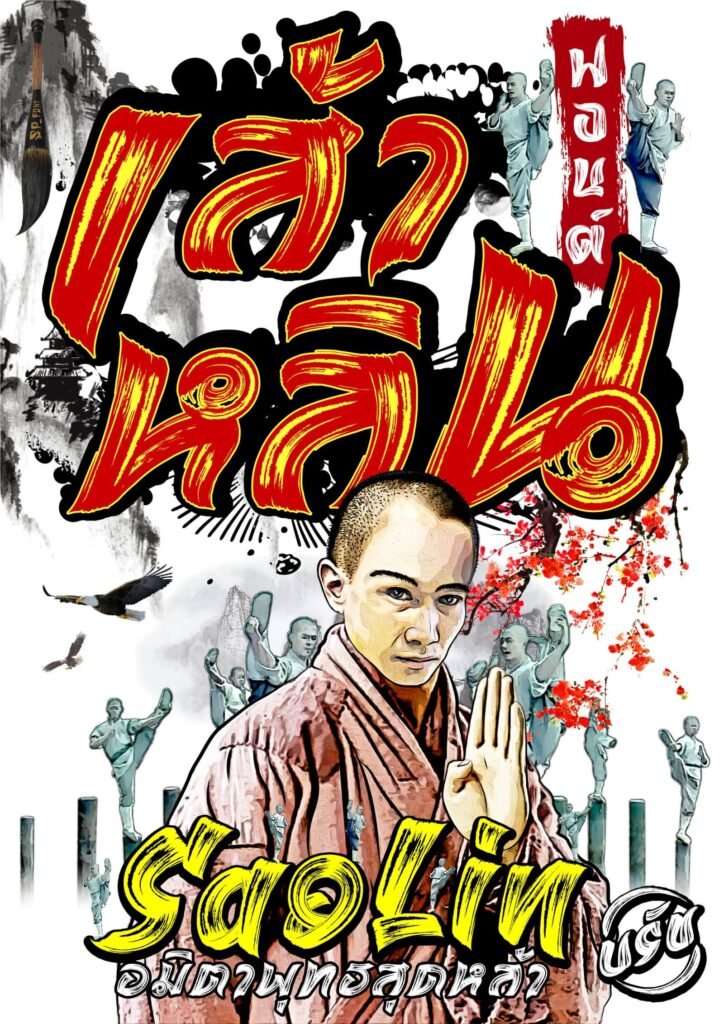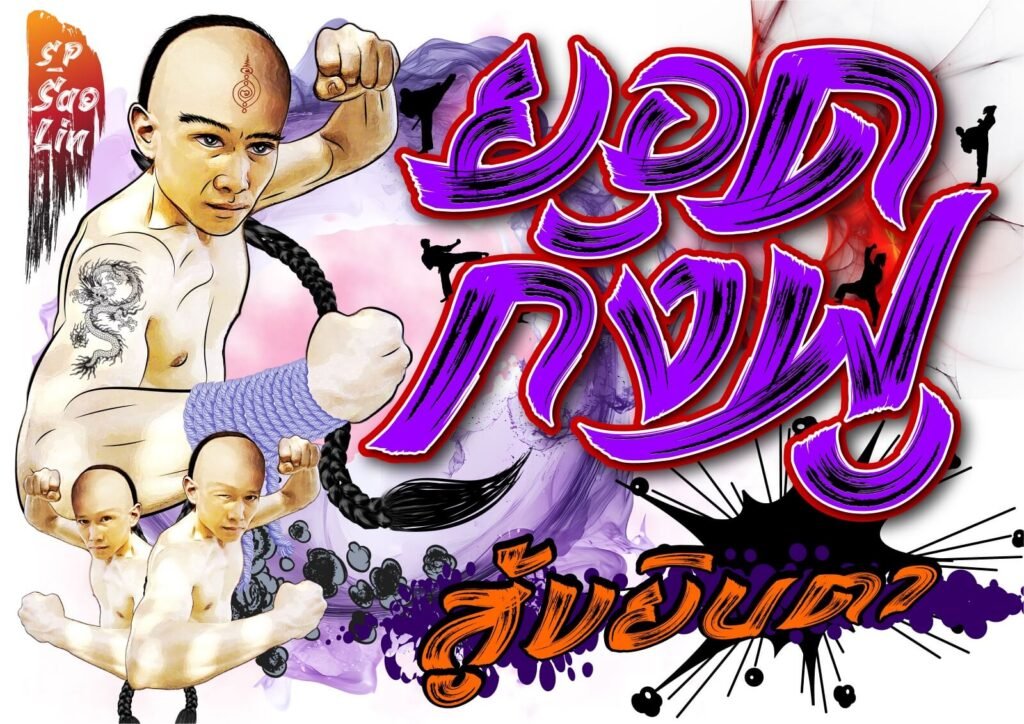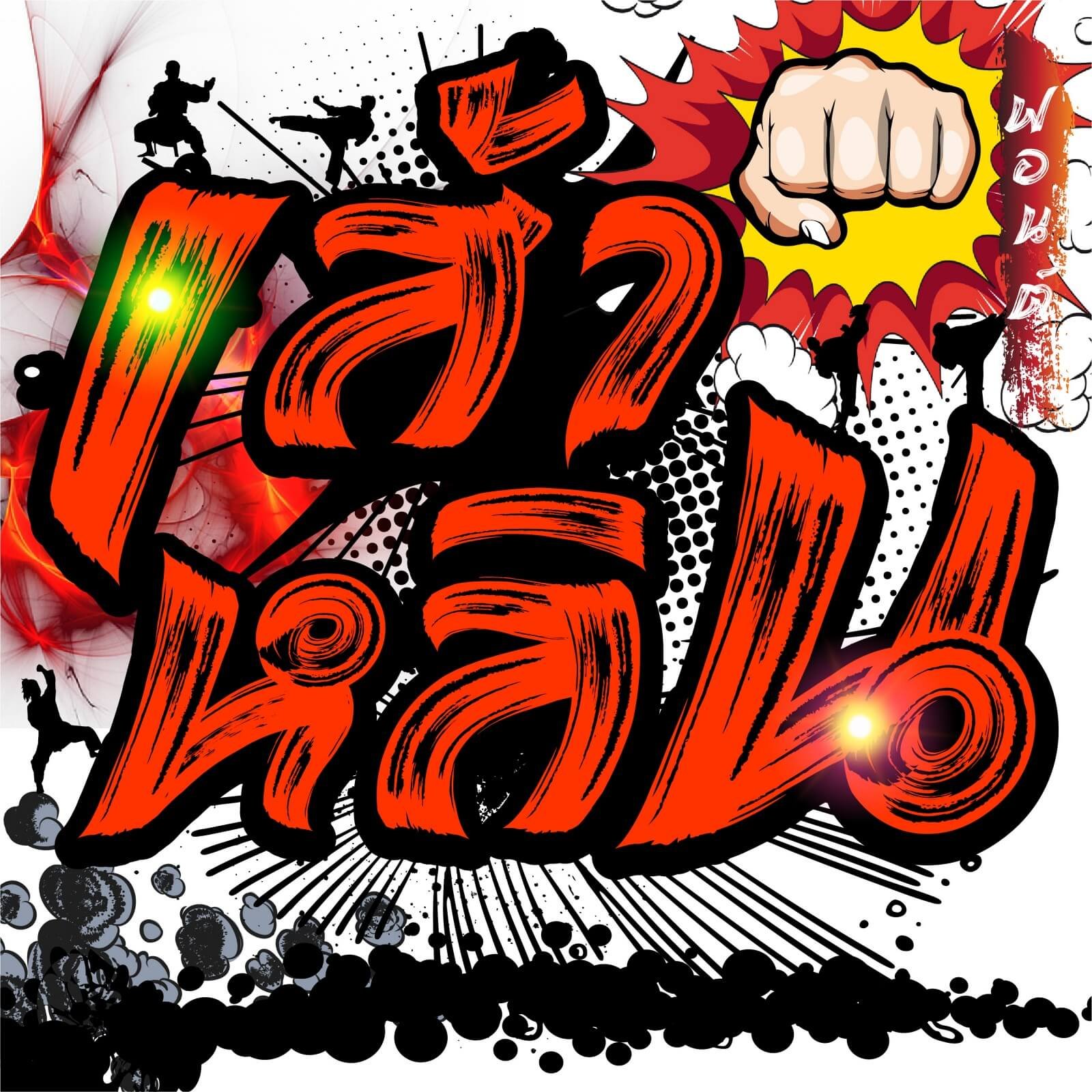
เส้าหลิน (SP_SaoLin)
เส้าหลิน (SP_SaoLin) หมัดบินทะลุเหล็ก – รำลึกนึกถึงหนังจีนกำลังภายใน แอคชั่นมันส์พะยะค่ะ แรงบันดาลใจของวัยเกินรุ่นหลายๆ คน ซึ่งปัจจุบันจะเน้นเป็น CG แฟนตาซี หล่อหลอมประสานเป็นฟอนต์เส้าหลิน-SaoLin